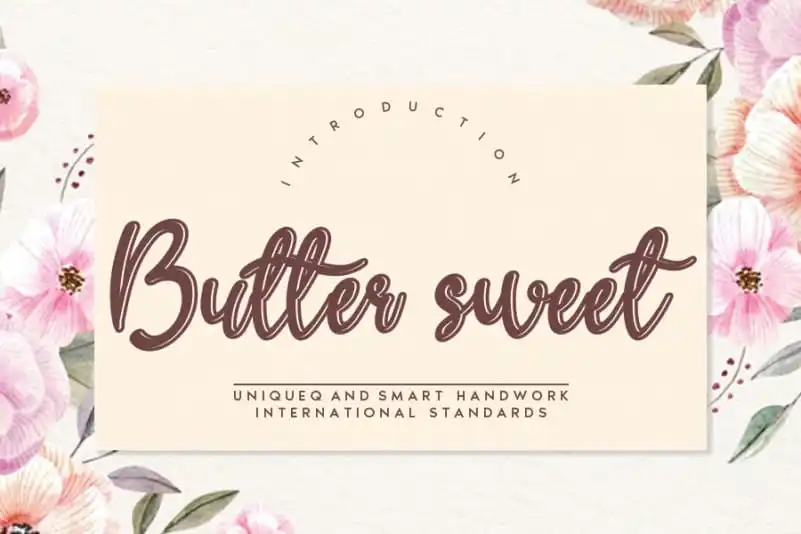
A Butter sweet Script Font é uma bela escolha para quem busca um estilo elegante e fluido na sua próxima obra de arte digital. Desenvolvida por andikastudio, esta fonte escrita à mão garante que seu design seja único e eterno. É perfeita para projetos pessoais e profissionais onde deseja manter uma personalidade especial. Perfumada e sofisticada como a própria palavra sugere, a Butter sweet Script é capaz de capturar sua imaginação com sua forma distintiva e autêntica. Não importa se está trabalhando em um projeto editorial, design gráfico ou criação web – esta fonte irá te ajudar a produzir resultados impressionantes. Seja você quem crie as melhores lembranças de seus projetos, essa font será sua companheira perfeita para criar designs surpreendentes e memoráveis.